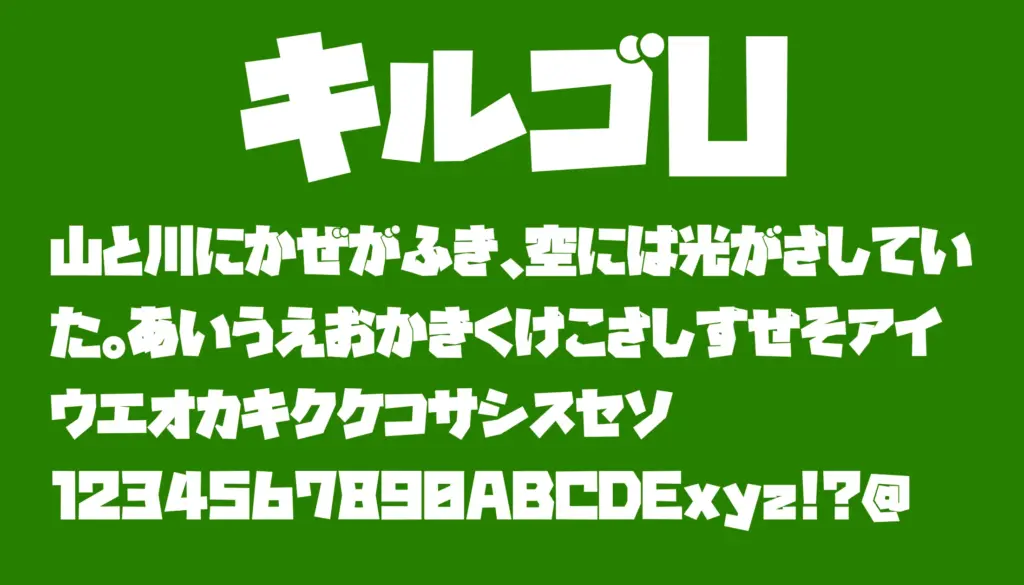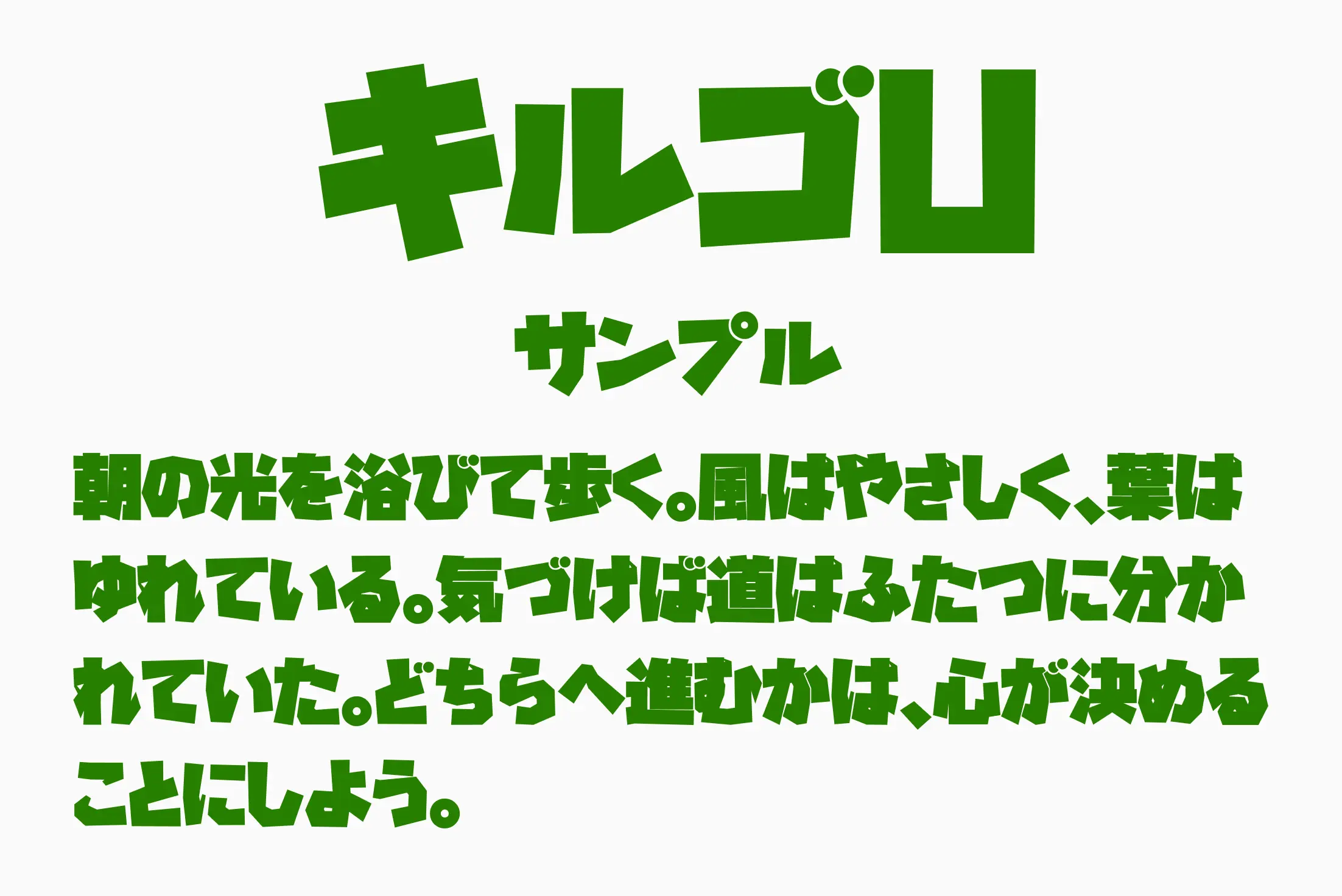
シンプルながら圧倒的な存在感を放つ、極太ゴシック体フォントです。
横幅のあるワイドな文字と、無機質かつ直線的なデザインが特徴で、視覚的なインパクトを与えるレイアウトにぴったり。もともとゲームやフライヤー、映像タイトルなどでの使用を意識した設計になっており、ロゴ・サムネイル・大型見出しでの使用に最適。
キルゴU